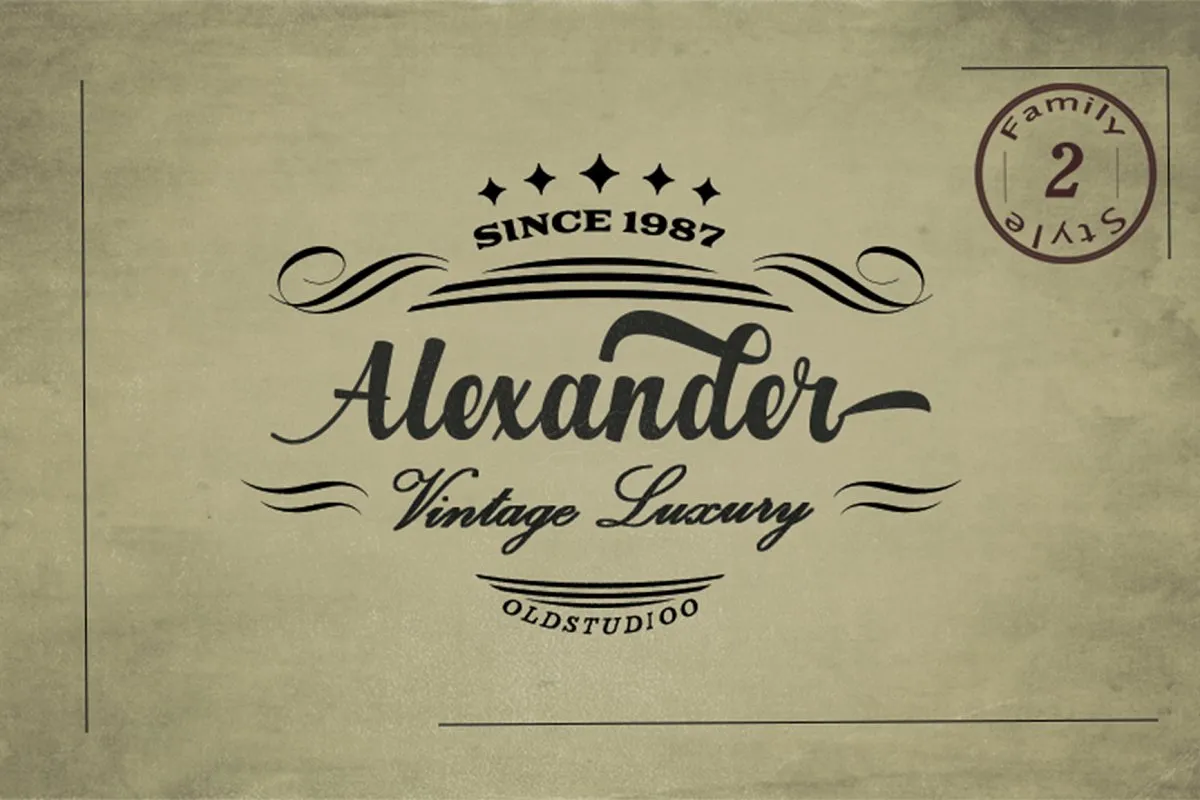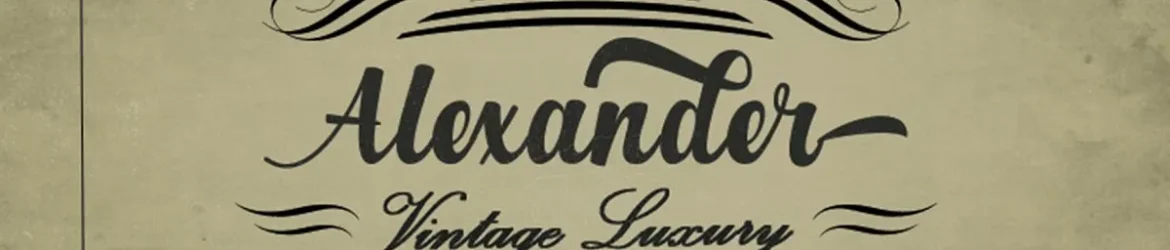
Olá amigos! Este é um tipo script elegante com uma aparência que remonta ao tempo. Introduzimos a Typeface Alexander. As fonts são criadas e compartilhadas pelo Old_Studio. A Alexandre é um tipo de caracteres script, com personalidade. Você pode usá-la como logomarca, estandarte, símbolo de marca, embalagem, cabeçalho, cartaz, camiseta/apparel, cartão de convite de casamento. Os caracteres flutuantes são perfeitos para fazer mensagens atraentes, misturando e combinando Montana com uma coleção diversificada de caracteres alternativos para atender ao seu projeto.